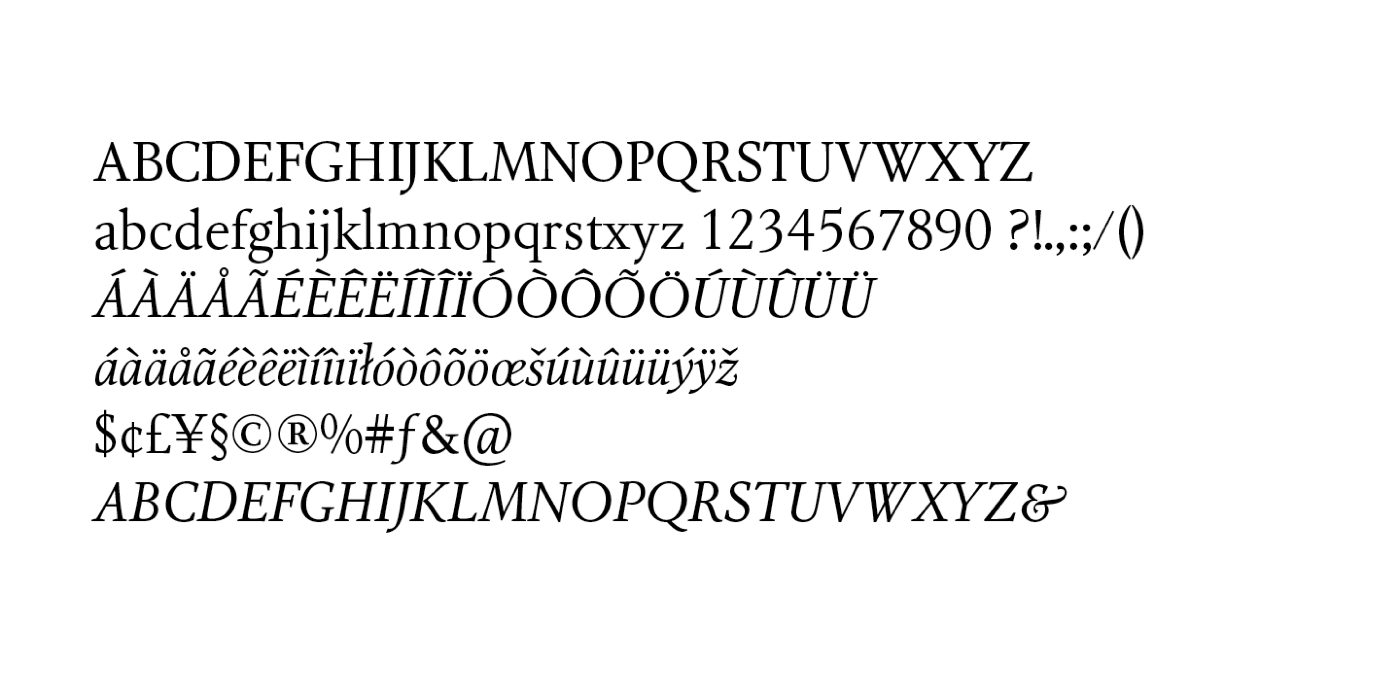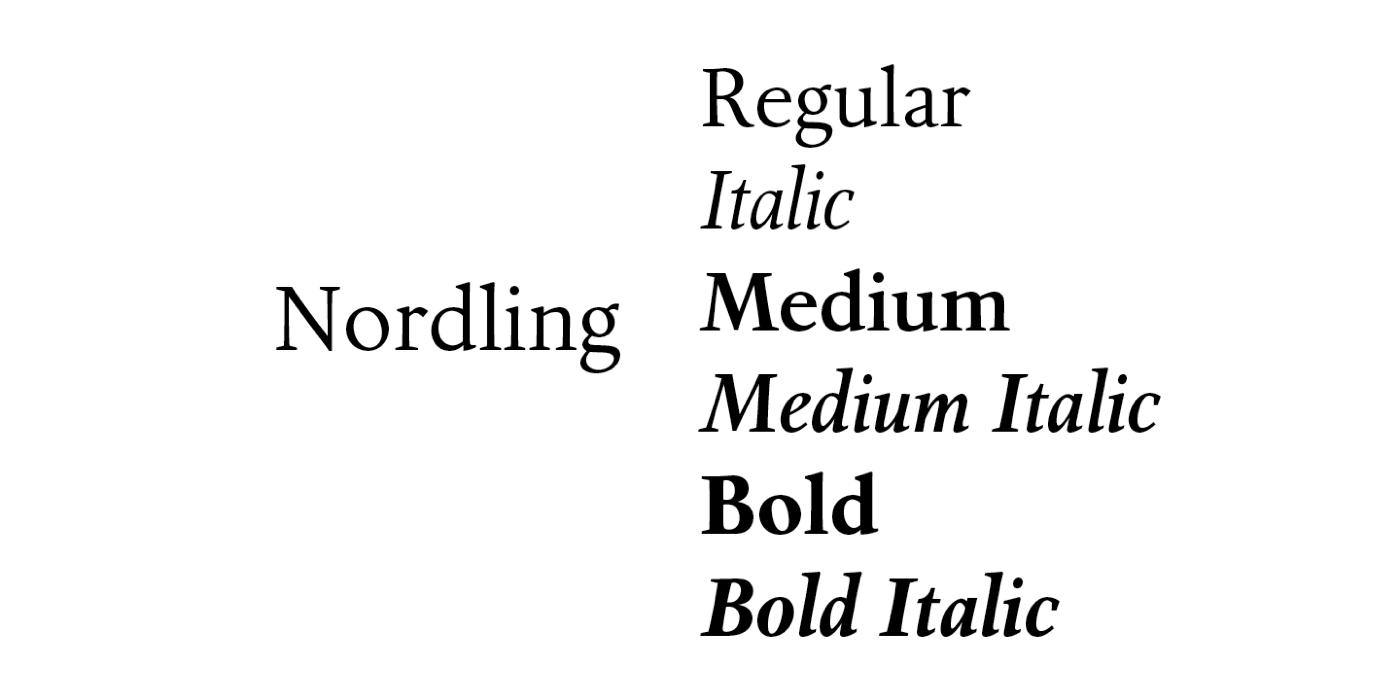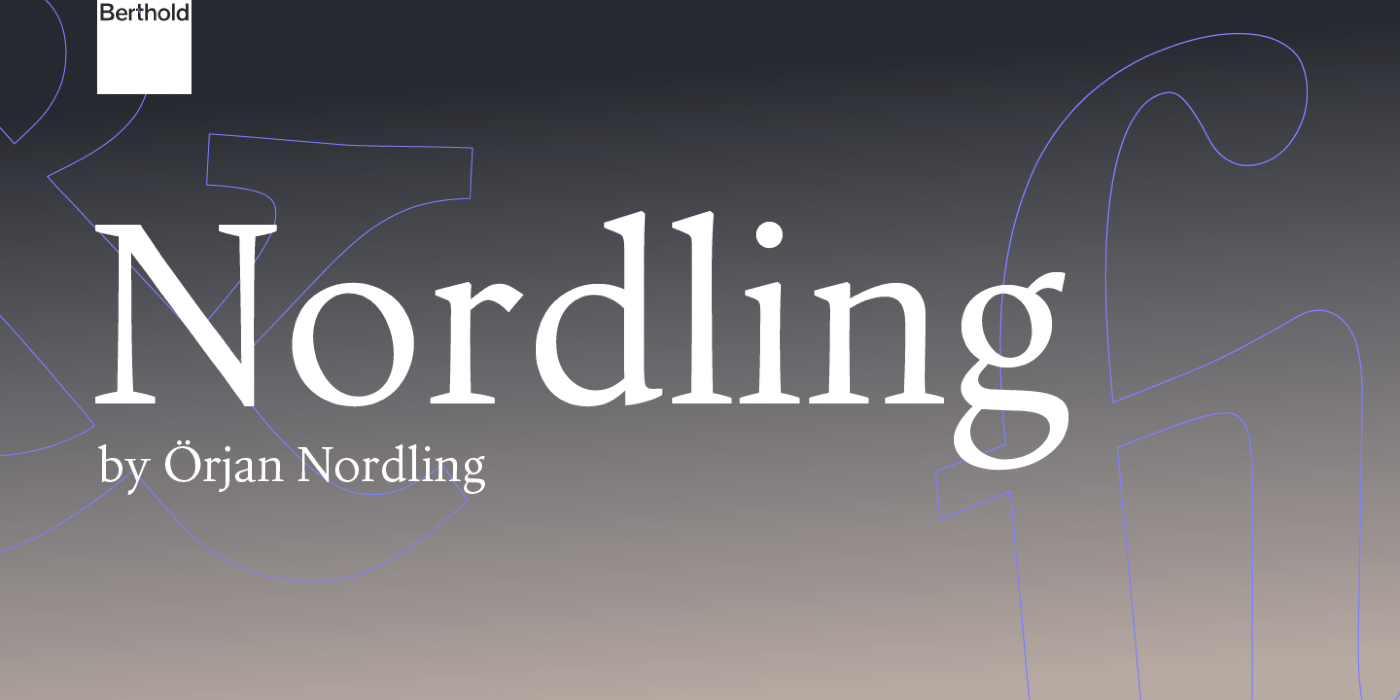
Die Antiqua-Familie Nordling, benannt nach ihrem Gestalter Örjan Nordling, erschien 1995 bei Berthold und ist heute über Monotype verfügbar. Die Familie besteht aus drei Strichstärken mit Kursiven in westeuropäischer Zeichenbelegung.